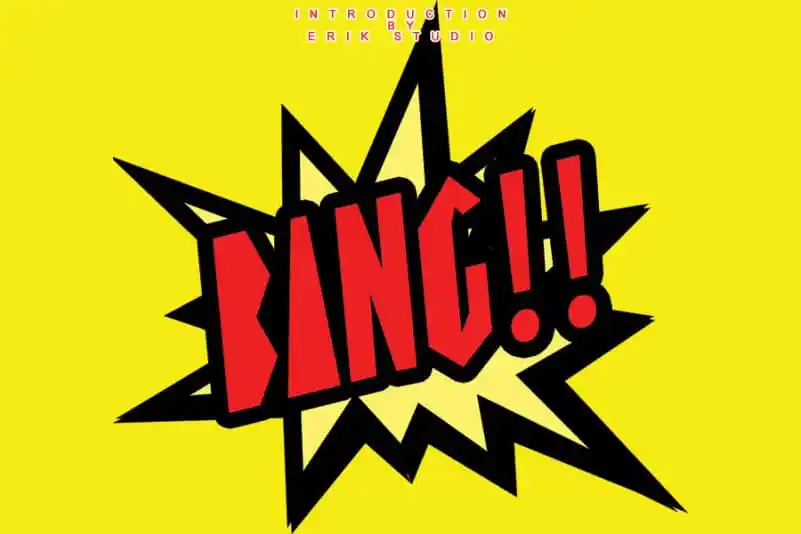
A fonte ‘BANG Display Font’ é uma escolha perfeita para designers que procuram algo diferente no seu trabalho. Ela se destaca com sua elegância e modernidade, incorporando um toque energético e único ao design de cada letra. Este tipo de fonte brinca com a tipografia, oferecendo uma sensação vibrante que irá revolucionar as suas criações. Adicione essa font especial aos seus projetos criativos e observe como ela faz sua obra se destacar dos demais. ‘BANG Display Font’ é ideal para designers que buscam dar um toque de personalidade inovadora à sua arte digital, transformando simples ideias em marcas memoráveis. Sempre pronto para aqueles que desejam trazer uma sensação fresca e contemporânea aos seus trabalhos visuais, esta fonte representa o futuro da tipografia.